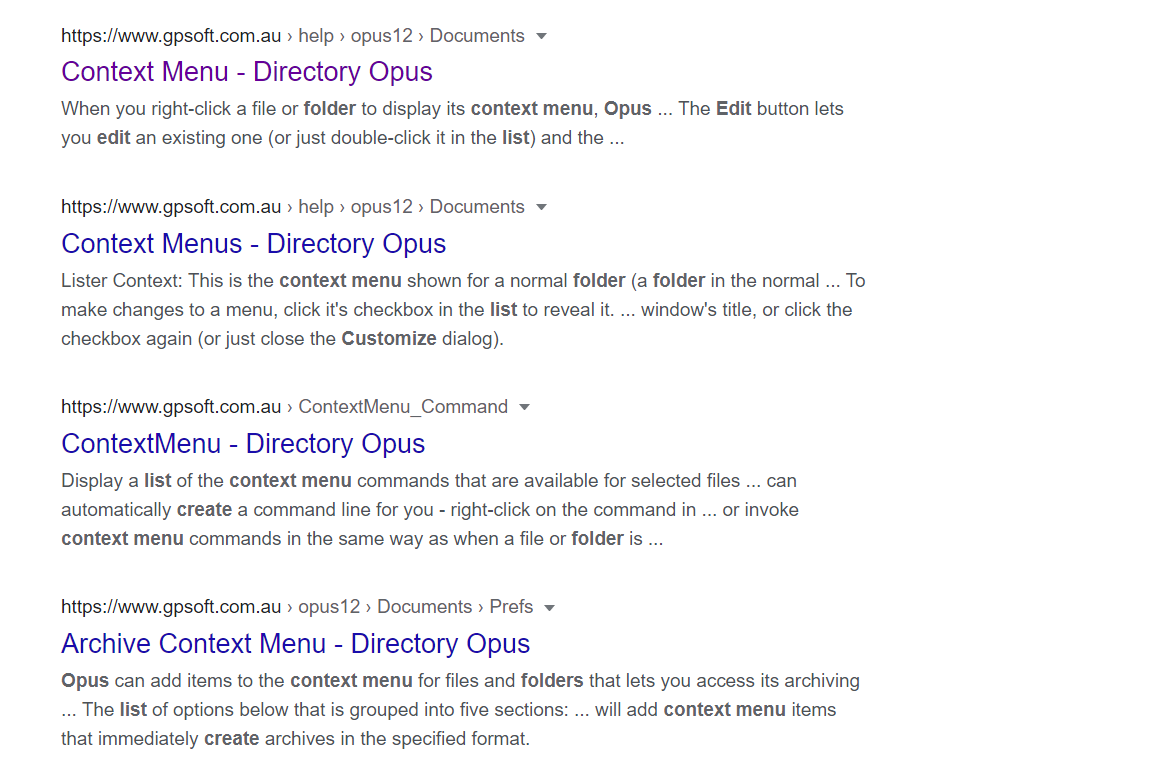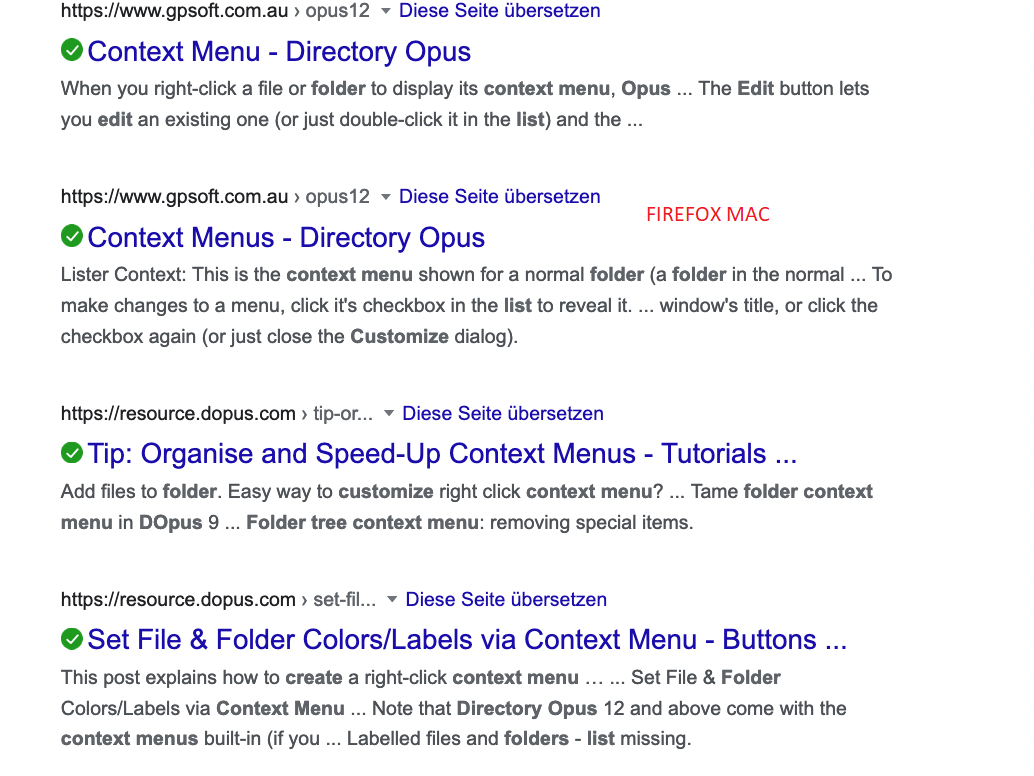
Schriftart Google in Edge für Windows vs. Firefox für Mac
ich nutze Parallels auf einem M1 Mac und mir ist aufgefallen, dass die Google-Ergebnisse in Edge(Win) eine angenehmere Schrift haben als in FF für Mac. Mein Eindruck ist, dass es jedes Mal Arial ist, aber Edge stellt es irgendwie klarer und feiner dar. Gibt es irgendeine Möglichkeit, das auch auf FF/Mac hinzukriegen?
Ändere mal in der about:config folgendes:
gfx.font_rendering.cleartype_params.enhanced_contrast 0
gfx.font_rendering.cleartype_params.rendering_mode 5
Dann sollte es glaube ich so wie in Chrome/Edge aussehen.